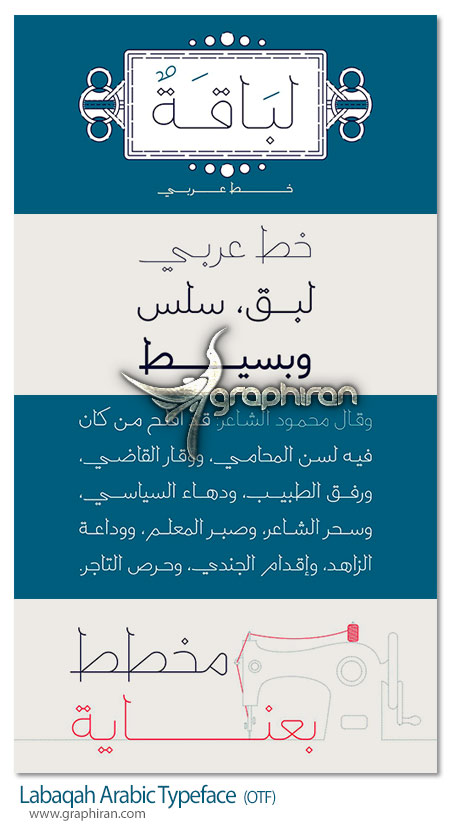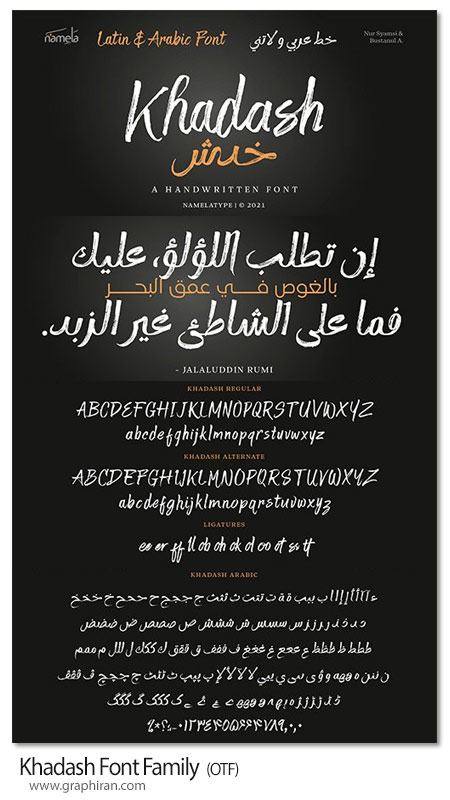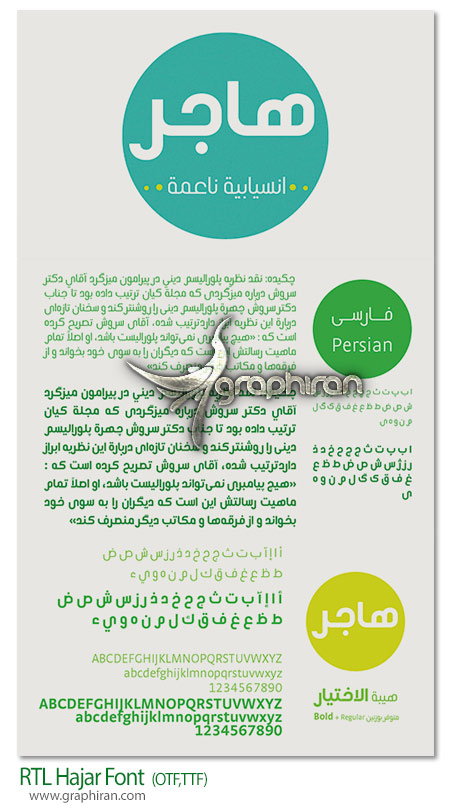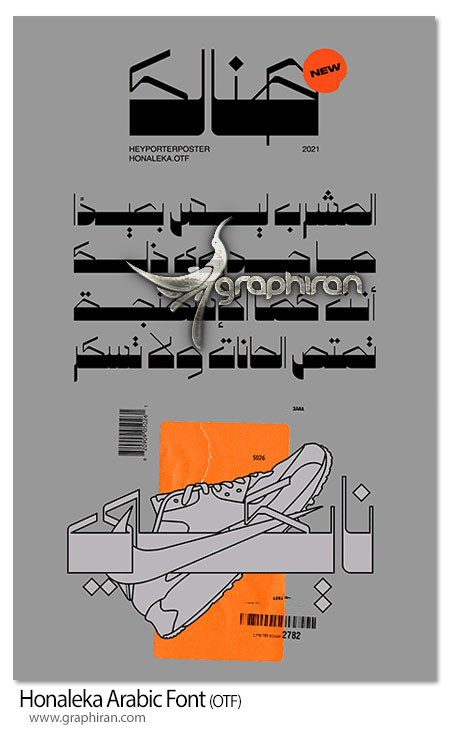
دانلود فونت عربی لباقه Labaqah Arabic Typeface لبقه، نام نوع حروف عربی است که سبک نسخ سنتی را با طعمی از خط دستی ساده ترکیب میکند. این نوع حروف شامل سه وزن (سبک، معمولی و پررنگ) است و برای برنامههای وب، چاپ و موبایل مناسب است.
فونت دست نویس خطاطی عربی و لاتین زهران Zahran Font Family – Latin & Arabic یک فونت لاتین و عربی دستنویسی زیباست که از سبک خطاطی مدرن الهام گرفته شده است. این فونت دارای ویژگیهای زیادی است، از جمله حروف جایگزین، نسخههای مختلف حروف (cv01 تا cv12)، لیگچرها، حروف چندزبانه، خط شروع و پایان زیبا و اتصالدهندههای دستنویسی برای حروف کوچک است که با استفاده از ویژگی opentype قابل دسترسی است. زهران برای پروژههای برندینگ، بستهبندی محصولات، عنوان، لوگو، عروسی، نقل قولها و هر جایی که به یک طراحی زیبا نیاز دارید، مناسب است.
دانلود فونت دست نویس عربی و لاتین خدش Khadash Font Family یک فونت لاتین و عربی با قلم نویسی براق است که با حرکات طبیعی شبیه به دستنویسی واقعی ساخته شده است. فونت عربی خداش جداگانه است و دارای زیر خانواده حروف لاتین برای کاهش اندازه فونت میباشد. دو مجموعه از حروف لاتین در قالب حروف، معمولی و جایگزین، وجود دارد. خداش برای پروژههای برندینگ، بستهبندی محصولات، کالای تبلیغاتی، نقل قولها و غیره مناسب است.
فونت فارسی، عربی، کردی و اردو الوجد HS Alwajd Font “Hs Alwajd” یک فونت عربی و فارسی است که در دسته بندی “عناوین” قرار دارد. این فونت برای عناوین کتاب، طرح های خلاقانه و لوگوهای مدرن مفید است. همچنین زمانی استفاده می شود که نیاز به یک ظاهر معاصر و ساده است که با ویژگی های کوفی فاتمیک که بخش های افقی آن برابر با بخش های عمودی آن هستند، سازگار باشد. این فونت بر اساس خطاطی کوفی فاتمیک به همراه برخی ایده های مشتق شده از فونت های تزئینی است، حفظ زیبایی فونت عربی و شکل های ثابت آن را دارد. بدون شک، قرار دادن تزئینات منحنی در برخی بخش ها، زیبایی و تنوع جذاب تری را در خط جریان بین بخش های تیز، نرم و منحنی اضافه می کند. این فونت از زبان عربی، فارسی، پشتو، کردی سورانی، کردی کرمانجی و اردو پشتیبانی می کند، و شامل تنها یک وزن است که می تواند به کتابخانه فونت های عربی کوفیک مدل های معاصر را اضافه کند که با هدف طراحی های مختلف برای همه منظوره ها و همه سلیقه ها قابل استفاده است.
دانلود فونت فارسی و عربی هاجر RTL Hajar Font یک فونت جذاب عربی و فارسی مناسب برای پاراگراف های طولانی الهام گرفته از خطوط کالیگرافیک عربی و گوشه های گرد که برای نوشتن من های روزنامه، کتاب و طراحی پوستر و کارت ویزیت می تواند انتخاب مناسبی باشد.
دانلود فونت عربی طالاما Talama Arabic Font یک فونت کلفت عربی دارای ظاهر هندسی مناسب برای ساخت تایتل و نوشتن عنوان مطالب و همینطور طراحی پوستر و لوگو می باشد که ظاهر قدیمی آن می تواند انتخاب مناسبی برای طراحی بنر و پوستر مذهبی نیز باشد.
دانلود فونت عربی هنالک Honaleka Arabic Font یک فونت عربی هندسی و فانتزی است که مناسب برای طراحی برندینگ، اینفوگرافی و طرح های گرافیکی مختلف می باشد. این فونت عربی جدید دارای ۱ ضخامت است و مناسب برای طراحی لوگو و لوگوتایپ نیز می باشد.